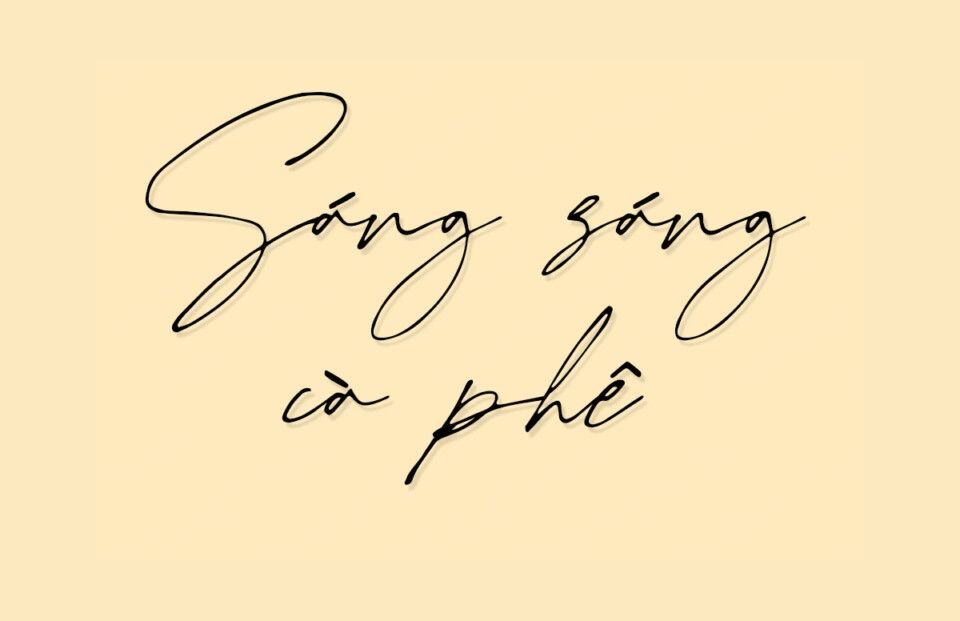
Font Việt hóa 1FTV VIP Barega là bộ phông chữ độc đáo và đẳng cấp, được thiết kế dành riêng cho cộng đồng nhà sáng tạo nghệ thuật và thiết kế đồ họa tại Việt Nam. Với sự hòa quyện tuyệt vời giữa phong cách thể hiện hiện đại và cấu trúc ký tự Tiếng Việt tinh tế, bộ font này mang đến một diện mạo mới mẻ cho mọi dự án. Dù bạn đang xây dựng nhận diện thương hiệu, thiết kế ấn phẩm truyền thông hay tạo hình bao bì sản phẩm, 1FTV VIP Barega chắc chắn sẽ là nguồn cảm hứng bất tận.
Font Việt hóa 1FTV VIP Barega – Nâng Tầm Typography Cho Dự Án Thiết Kế Đồ Họa Modern
Trong thế giới thiết kế đồ họa đa dạng ngày nay, typography không đơn thuần là việc chọn chữ để ghi nội dung, mà nó còn là tiếng nói thị giác, truyền tải cảm xúc và định hình phong cách cho toàn bộ tác phẩm. Font Việt hóa 1FTV VIP Barega được ra đời nhằm giải quyết triệt để bài toán tìm kiếm một phông chữ vừa mang tính nghệ thuật cao, vừa thể hiện mượt mà các dấu thanh Tiếng Việt. Với các nét chữ được chăm chút tỉ mỉ, bộ font chữ này thể hiện rõ sự cân bằng hoàn hảo giữa tính thẩm mỹ thời thượng và khả năng ứng dụng thực tế cao.
Điểm đặc biệt khiến 1FTV VIP Barega trở thành sự lựa chọn ưu tiên của nhiều designer chuyên nghiệp chính là thần thái tự tin, sang trọng nhưng không kém phần phá cách. Khi ứng dụng vào các tiêu đề lớn hay các cụm từ điểm nhấn, phông chữ ngay lập tức thu hút ánh nhìn của khán giả, tạo nên sự khác biệt rõ nét so với các font chữ tiêu chuẩn thông thường. Ngoài ra, việc Việt hóa chỉn chu giúp font hoạt động trơn tru trên mọi ngữ cảnh văn bản tiếng Việt mà không gặp bất kỳ lỗi hiển thị hay mất cân đối dấu nào.
Các Tính Năng Vượt Trội Của Font Việt hóa 1FTV VIP Barega
1. Đường Nét Thiết Kế Phá Cách Và Thẩm Mỹ Thị Giác Cao
Font Việt hóa 1FTV VIP Barega sở hữu ngôn ngữ thiết kế độc đáo với những đường cong uốn lượn đầy tính nghệ thuật kết hợp cùng các góc nét sắc sảo. Sự tương phản giữa nét dày và nét mỏng được tính toán kỹ lưỡng, tạo nên nhịp điệu thị giác sống động và cuốn hút. Điều này giúp bộ font dễ dàng tạo dựng chiều sâu cho các tiêu đề (headline), câu khẩu hiệu (slogan) hay các đoạn chữ nghệ thuật. Bản thân từng ký tự trong Barega đã là một tác phẩm thiết kế độc lập, cho phép người dùng biến tấu đa dạng mà vẫn giữ được sự thống nhất trong tổng thể tác phẩm.
2. Bộ Dấu Tiếng Việt Được Việt Hóa Tỉ Mỉ Và Cân Bằng Chuẩn Xác
Một trong những rào cản lớn nhất khi sử dụng font chữ nước ngoài là các dấu thanh Tiếng Việt thường bị đè nét, dính vào chữ hoặc làm phá vỡ tỷ lệ nguyên bản của font. Với 1FTV VIP Barega, toàn bộ hệ thống dấu thanh như sắc, huyền, hỏi, ngã, nặng cùng các dấu phụ như ê, ô, ơ, ư đều đã được tinh chỉnh thủ công bởi đội ngũ thiết kế giàu kinh nghiệm. Vị trí, kích thước và độ nghiêng của dấu được đặt một cách tự nhiên, hài hòa với thân chữ, đảm bảo khả năng đọc tốt ngay cả ở kích thước hiển thị nhỏ mà vẫn giữ nguyên được thần thái cao cấp của font nguyên gốc.
3. Hệ Thống Ký Tự Thay Thế Stylistic Sets Và OpenType Features Phong Phú
Được tích hợp công nghệ OpenType hiện đại, Font Việt hóa 1FTV VIP Barega mang đến kho ký tự thay thế (Alternate Characters), ký tự nối (Ligatures) và các đường nét trang trí (Swashes) vô cùng phong phú. Điều này cho phép các nhà thiết kế tự do sáng tạo, biến hóa các chữ cái đầu câu hoặc cuối từ thành những điểm nhấn nghệ thuật riêng biệt. Việc tùy biến typography cho logo hay tiêu đề sách, tạp chí trở nên nhanh chóng và linh hoạt hơn bao giờ hết mà không cần phải vẽ lại bằng tay (vectorize) một cách tốn thời gian.</p>
4. Khả Năng Tương Thích Hoàn Hảo Trên Đa Dạng Phần Mềm Và Nền Tảng
5. Ứng Dụng Linh Hoạt Trong Nhiều Ngành Nghề Và Lĩnh Vực Sáng Tạo
Không bị giới hạn trong một phong cách cố định, 1FTV VIP Barega là một công cụ đa năng phù hợp cho vô số lĩnh vực thiết kế khác nhau. Từ ngành thời trang cao cấp, mỹ phẩm, trang sức, bất động sản cho đến các ấn phẩm sự kiện, bìa sách, poster phim hay bao bì sản phẩm cao cấp, bộ phông chữ này đều hoàn thành xuất sắc vai trò nâng tầm giá trị thương hiệu. Sự hiện diện của 1FTV VIP Barega giúp các thiết kế vừa thể hiện sự sang trọng, hiện đại vừa giữ được yếu tố gần gũi, tinh tế đối với người xem Việt Nam.
Ứng Dụng Thực Tế Của Font 1FTV VIP Barega Trong Thiết Kế
Để khai thác tối đa tiềm năng của bộ phông chữ này, các nhà thiết kế có thể ứng dụng 1FTV VIP Barega vào các hạng mục sáng tạo đa dạng như:
- Thiết kế Logo & Bộ Nhận Diện Thương Hiệu: Tạo nên những biểu tượng chữ (Wordmark) sang trọng, mang dấu ấn riêng biệt cho thương hiệu.
- Ấn Phẩm Quảng Cáo & Marketing: Sử dụng cho các banner quảng cáo, poster sự kiện, brochure, standee nhằm thu hút ánh nhìn tức thì của khách hàng.
- Bao Bì Sản Phẩm: Làm nổi bật tên sản phẩm trên bao bì mỹ phẩm, chai vang, hộp quà tặng cao cấp, tạo cảm giác đắt giá và chỉn chu.